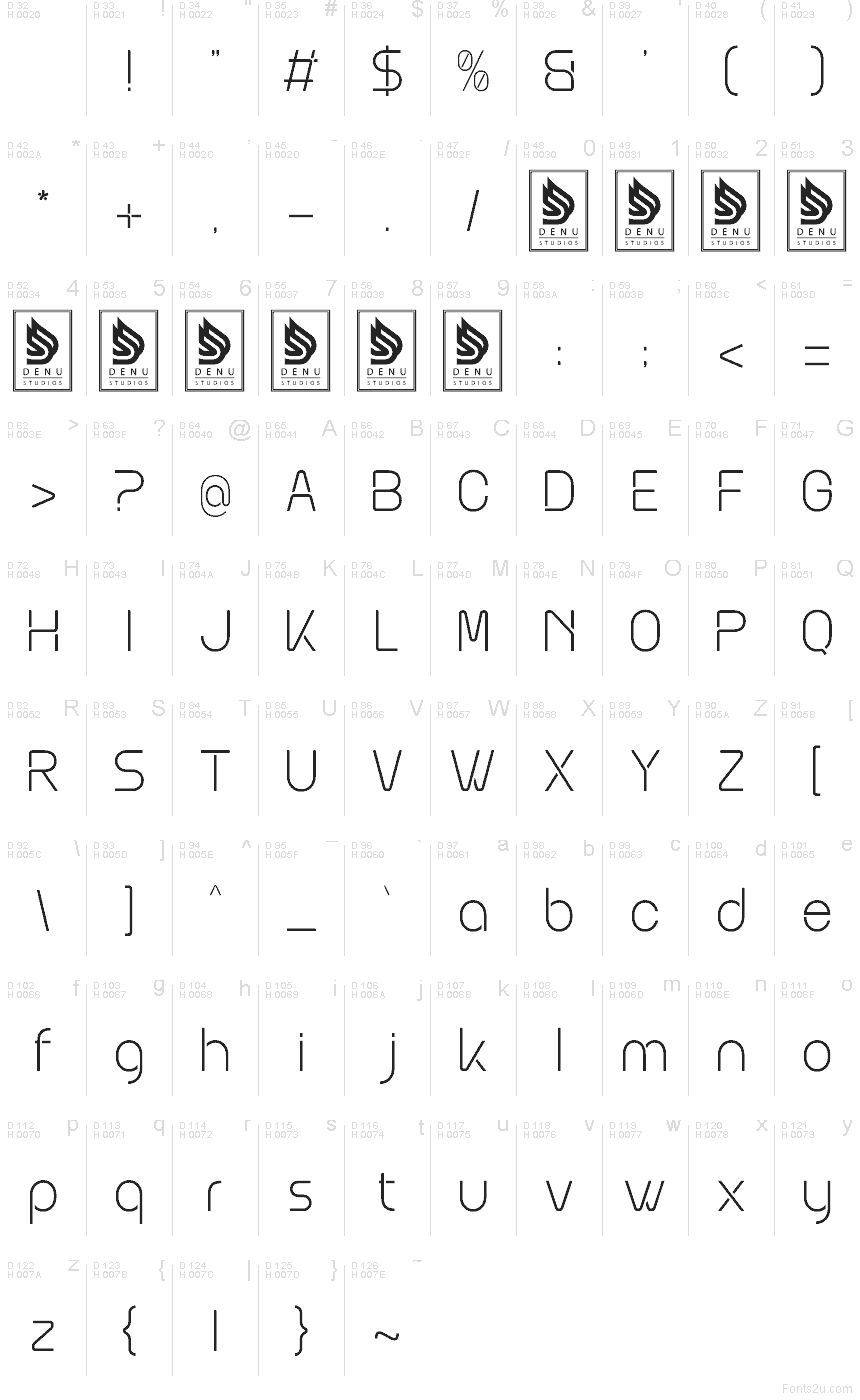
Neexan od Denustudios je bezplatné futuristické titulkové písmo s hladkým monoline vzhledem a střídmým geometrickým rytmem. Písmena působí vzdušně a technicky, kombinují zaoblené tvary s ostrými diagonálami, takže text působí čistě, ale lehce experimentálně.
Přirozeně zapadne do technologického brandingu, hudebních vizuálů, úvodních obrazovek aplikací, titulků na plakátech a nápisů, kde bezplatné písmo vnese elegantní, futuristickou atmosféru bez zbytečného vizuálního šumu. Díky jednoduchým a otevřeným tvarům funguje Neexan skvěle i v krátkých nadpisech, logách a monogramových iniciálách, které vyžadují klidný sci-fi nádech.